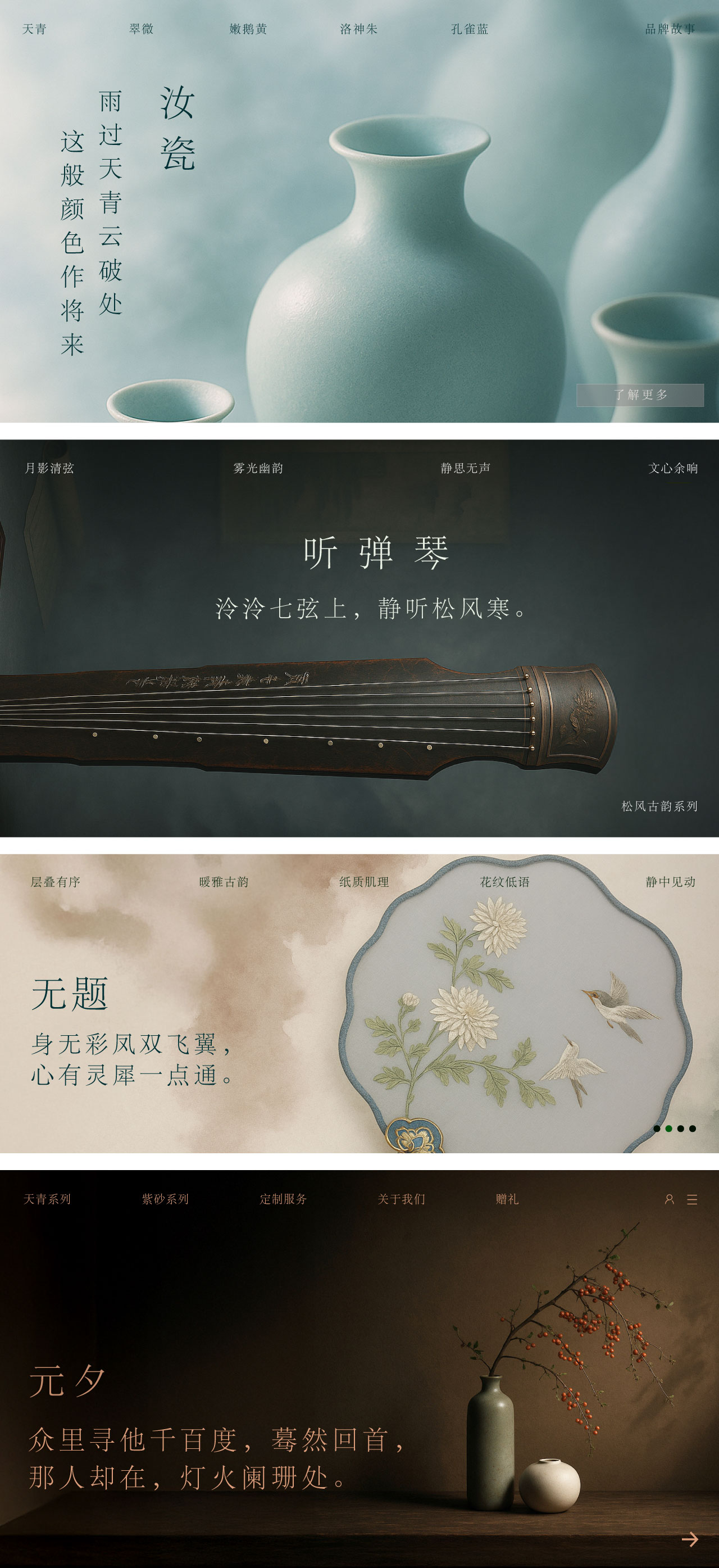
华文宋体 / STSongti / Light
华文宋体
在有限的空间进行无限分割
华文宋体 / STSongti
设计师:
常州华文
字体介绍:
华文宋体,雅致大方,字形具有一种方正雅观的特点,结构条理清晰;字符覆盖面广,覆盖了绝大部分汉字,包括一些生僻字;华文宋体的小字体清晰,可以清晰到12号字,而不失字体特点。
适用于商标设计、广告设计、报纸与图书等行业中,效果较好。